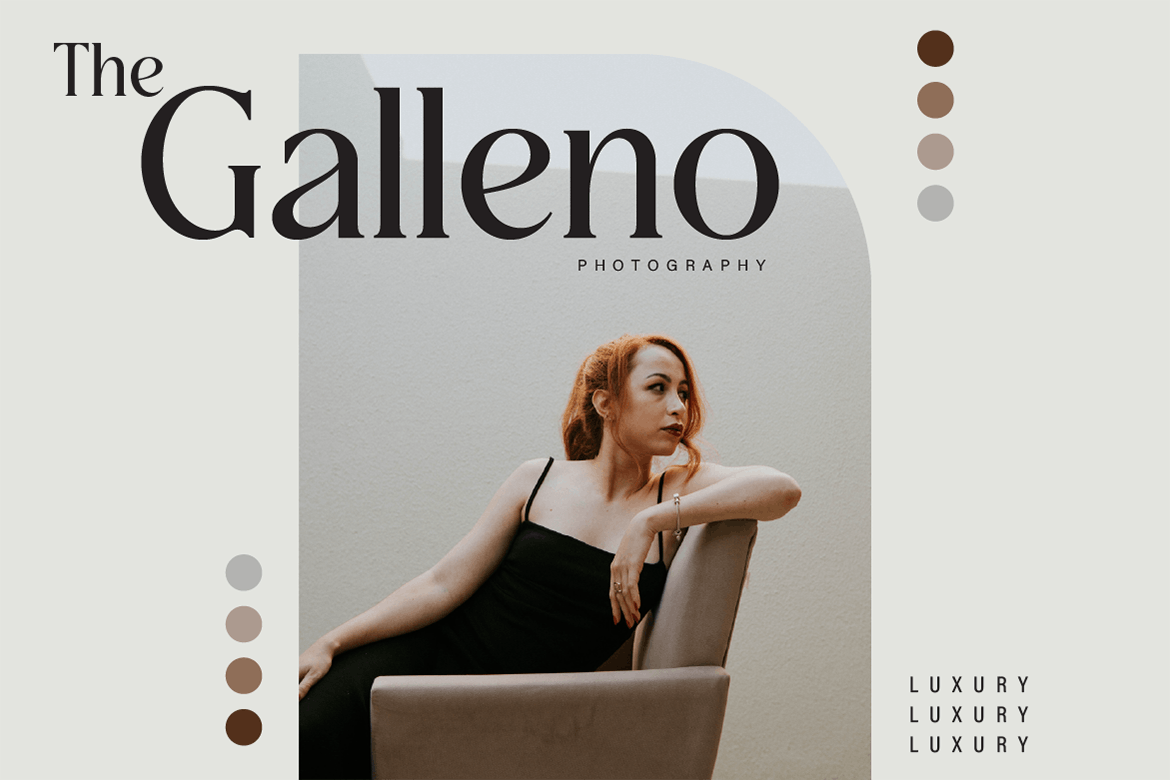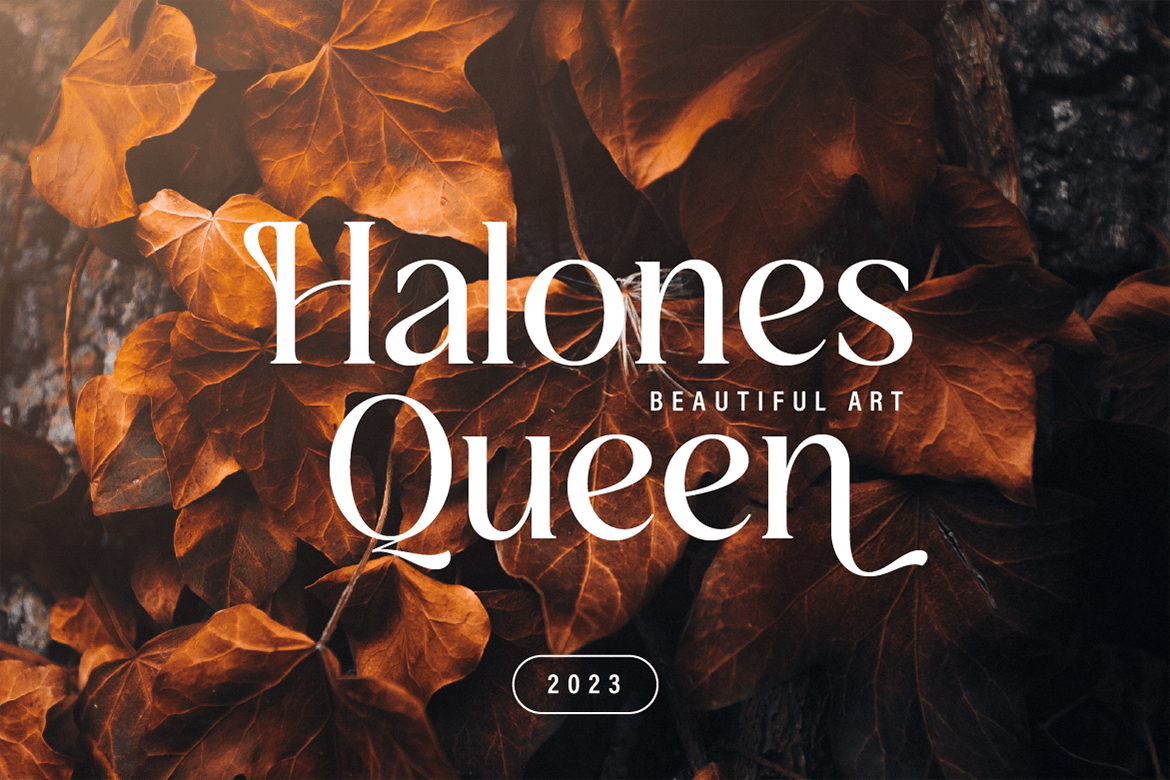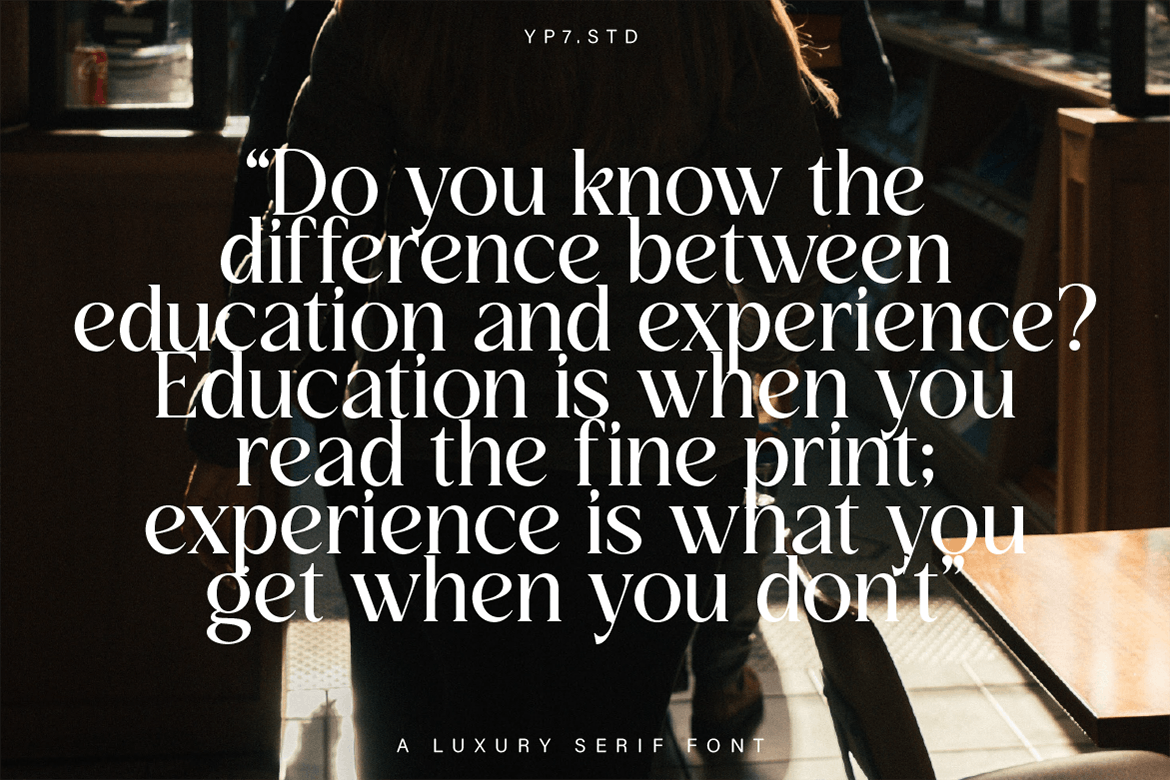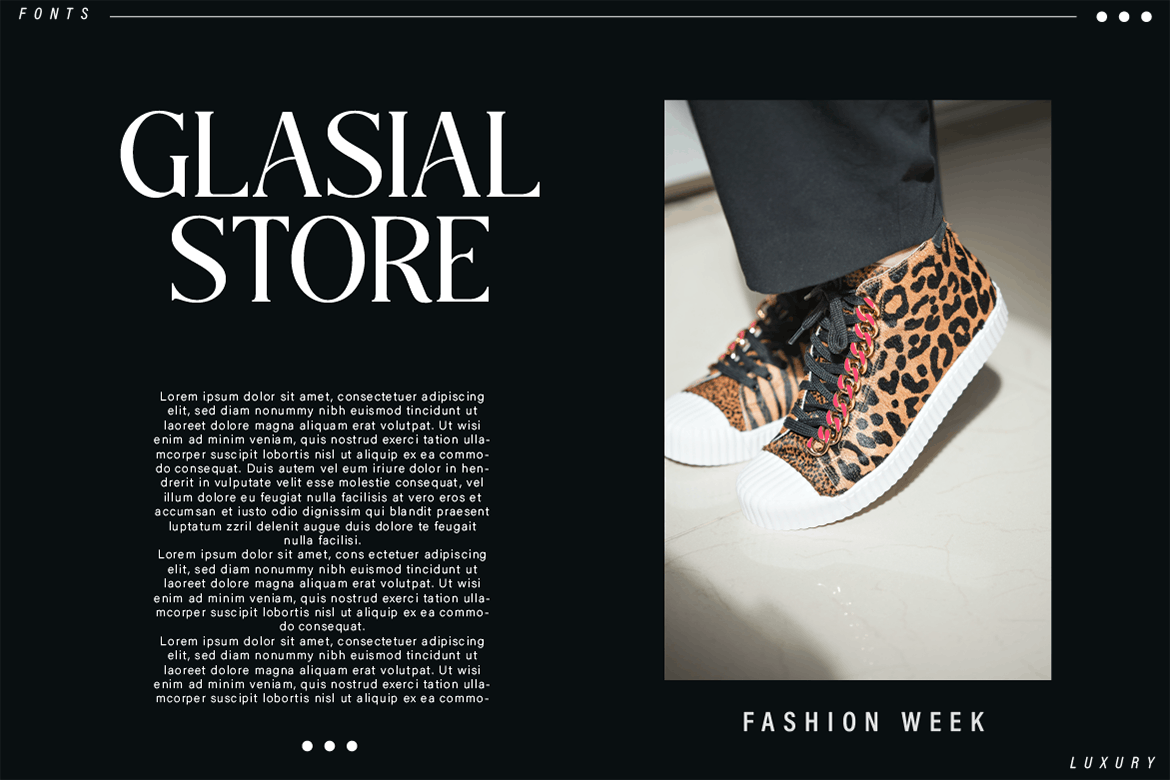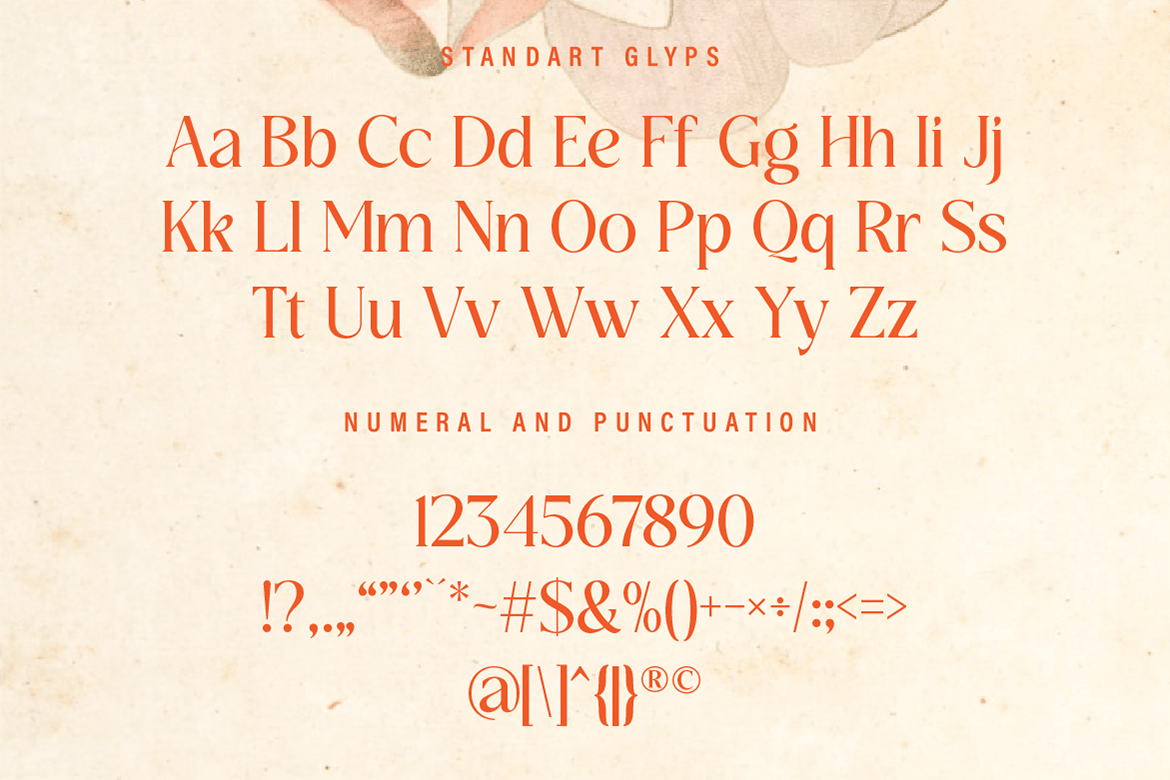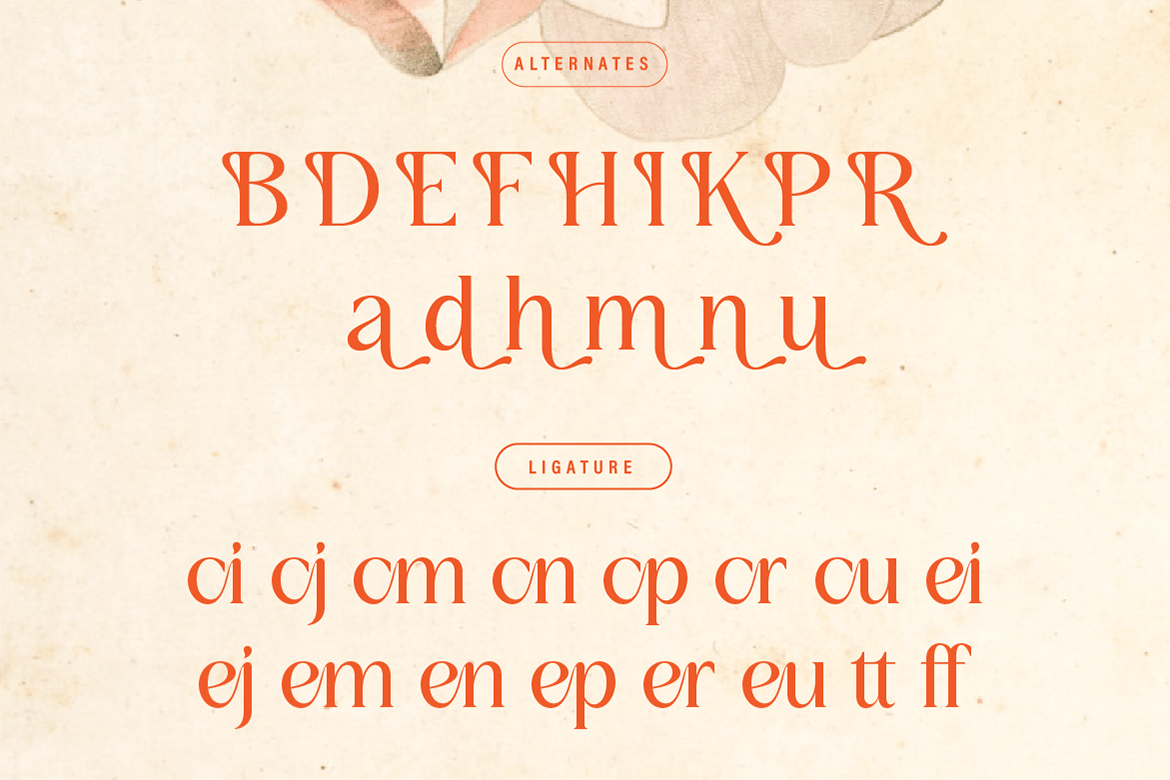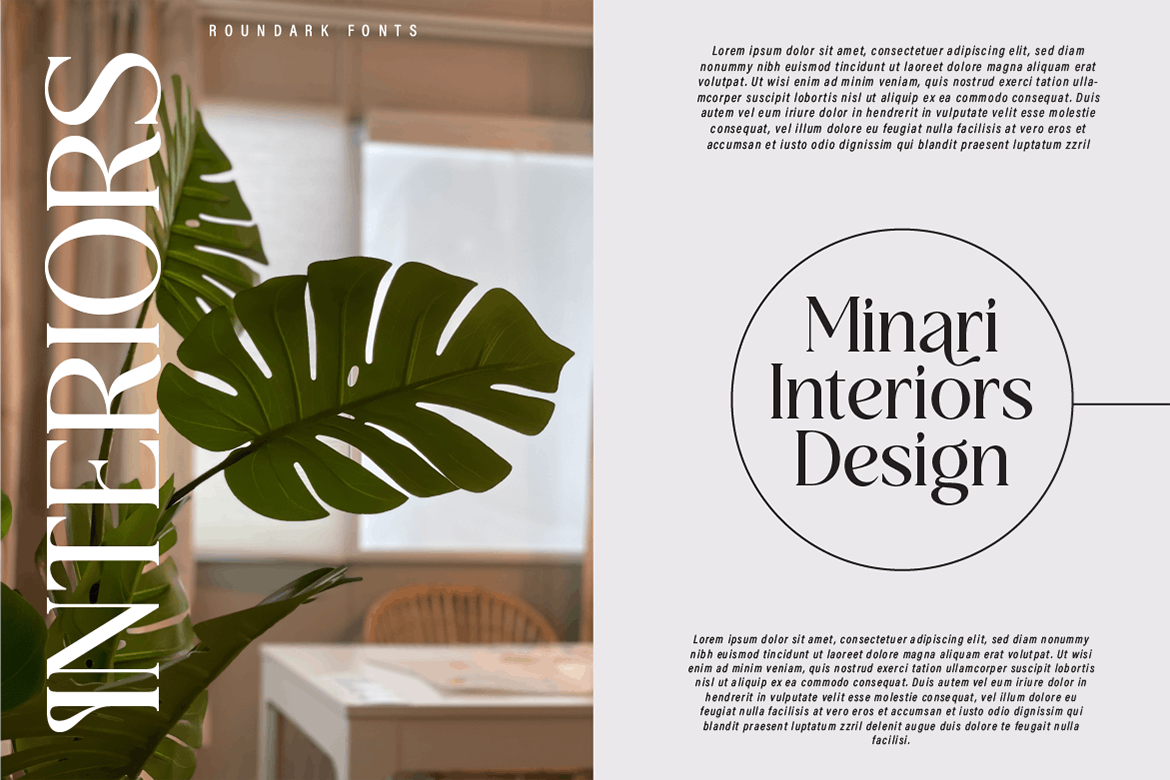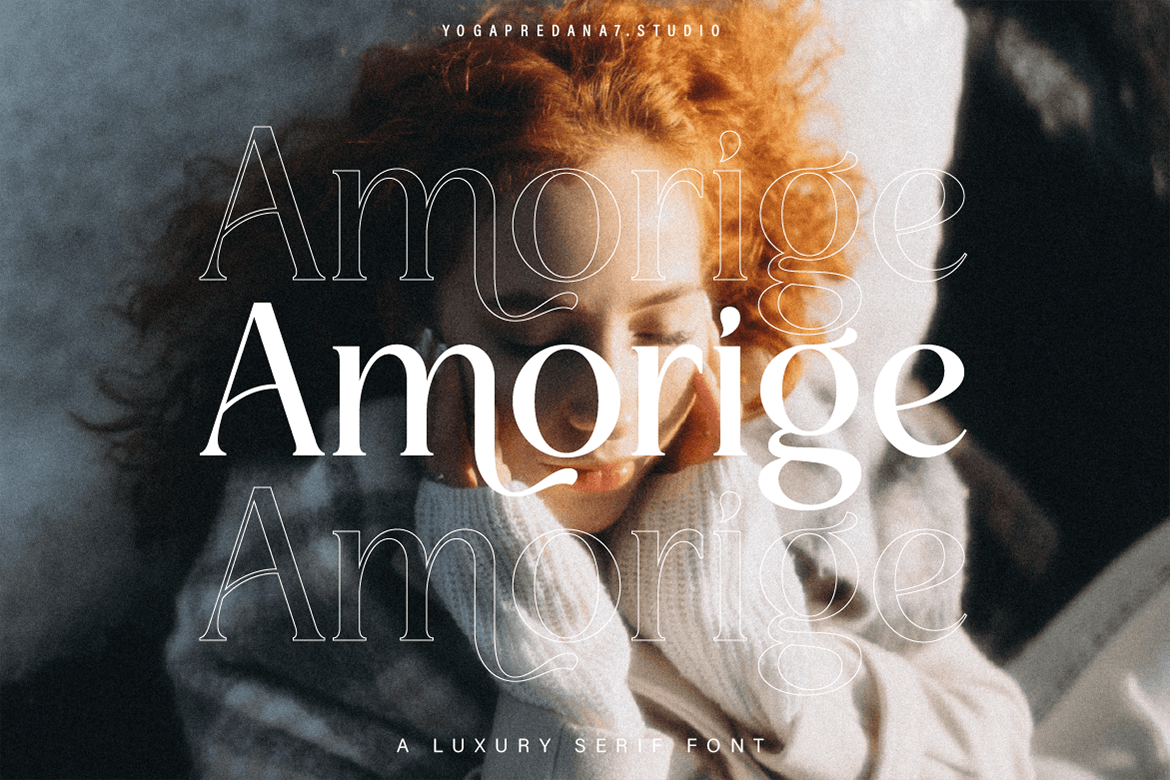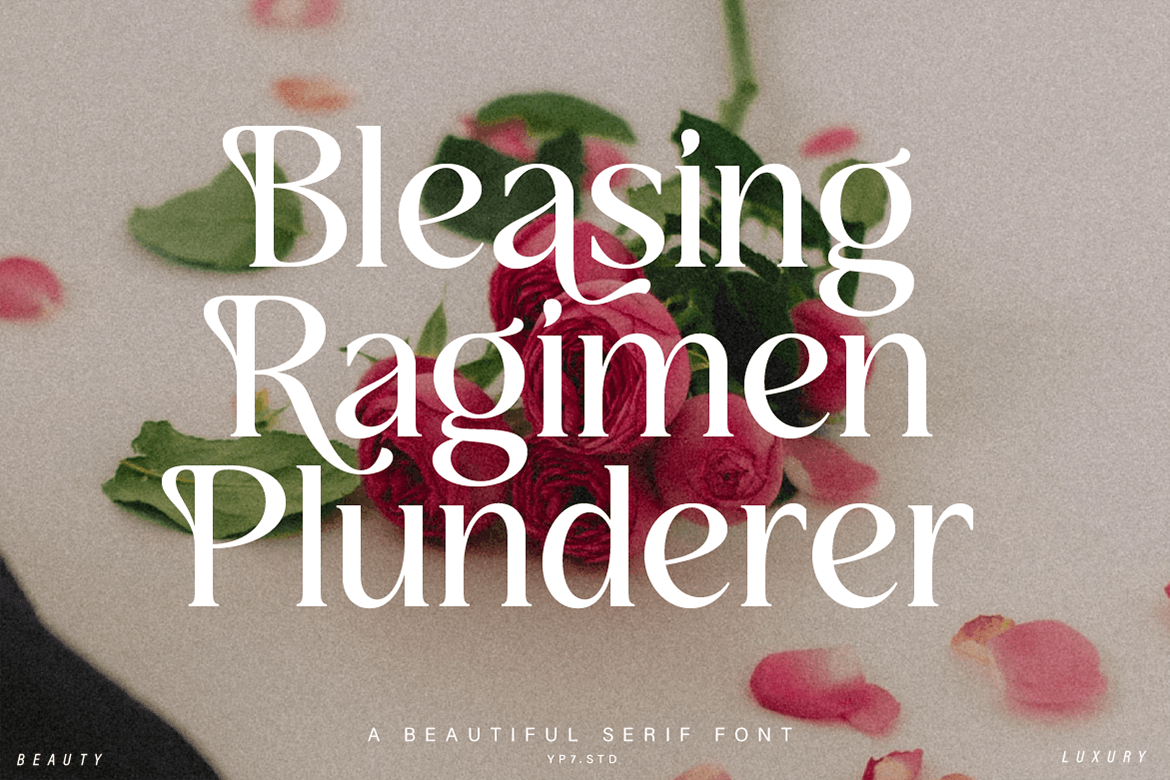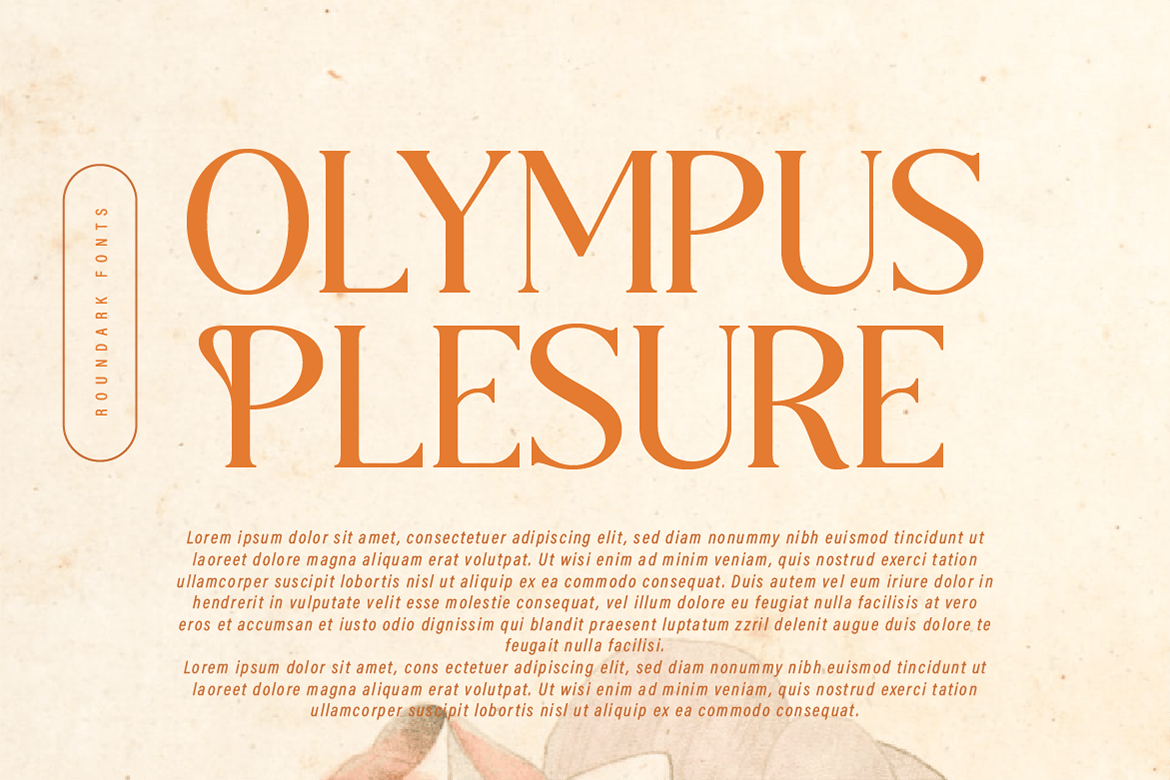
Luxury Serif Font
فونت سریف لوکس Roundark برای طراحی‌های خاص و حرفه‌ای مناسب است.
فونت سریف لوکس Roundark یک انتخاب عالی برای طراحان است که به دنبال ظاهری شیک و مدرن هستند. این فونت با طراحی منحصر به فرد و زیبا، می‌تواند جلوه‌ای خاص به پروژه‌های شما ببخشد.
• حروف بزرگ
• حروف کوچک
• اعداد و نشانه‌گذاری